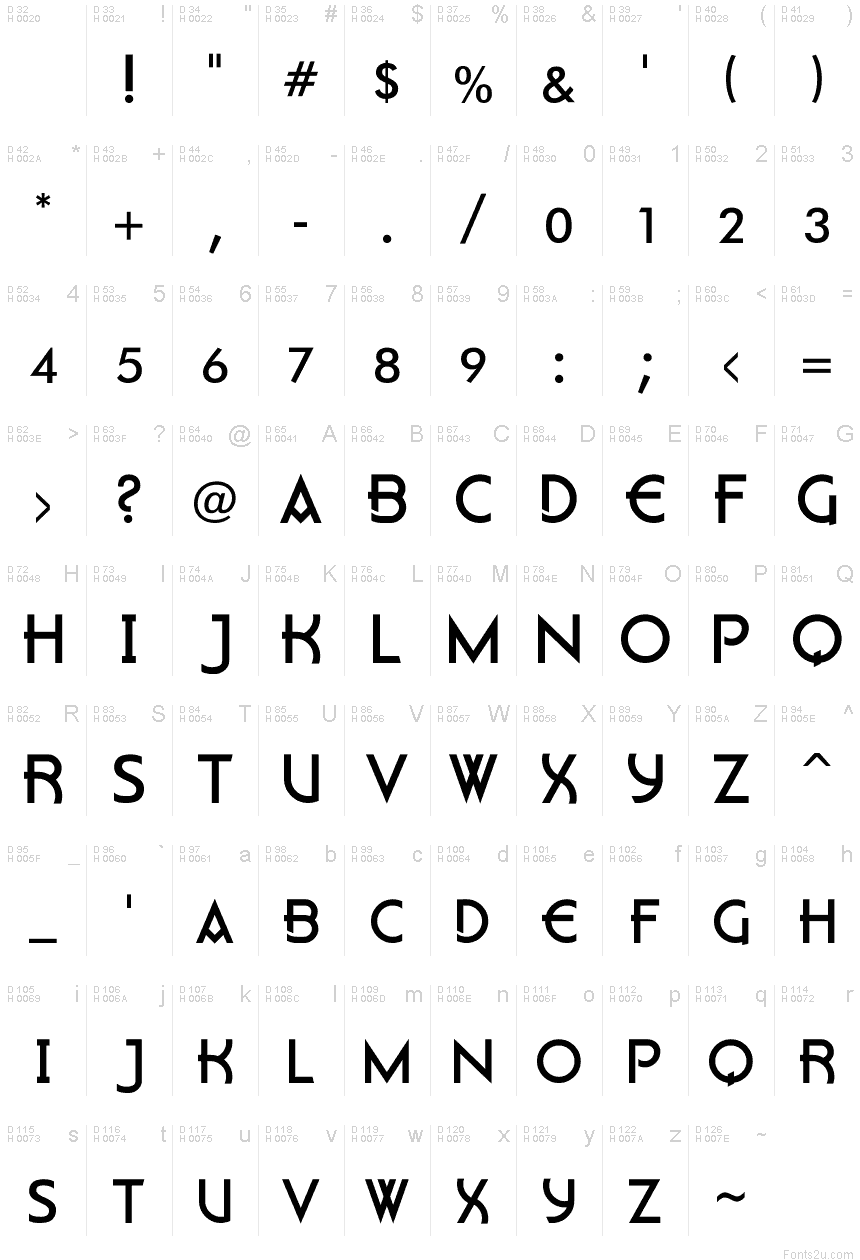
Flatley to darmowy, utrzymany w stylu retro krój displayowy, który przykuwa uwagę wysokimi, monolitycznymi literami i ostrymi kątami. Pogrubione pionowe kreski, klinowate zakończenia i wyraziste wewnętrzne wycięcia nadają każdemu słowu odważny, niemal futurystyczny charakter, przywodzący na myśl zabytkowe neony. Solidny, blokowy rytm sprawia, że krój pozostaje czytelny nawet w najbardziej szalonych projektach, zachowując przy tym mocny, wyrazisty styl wyraźnie inspirowany latami 70. i 80.
Flatley sprawia, że nagłówki zyskują silny poziomy impet, który świetnie sprawdza się na plakatach, mocnych logotypach, ulotkach, okładkach albumów, opakowaniach i grafikach do mediów społecznościowych. Ten darmowy font najlepiej prezentuje się w dużych rozmiarach, gdzie jego geometryczne detale i pełne, czarne kształty mogą w pełni wybrzmieć. Zestaw go z prostym, neutralnym krojem bezszeryfowym w tekście głównym i pozwól, aby Flatley grał pierwsze skrzypce w najważniejszych momentach.